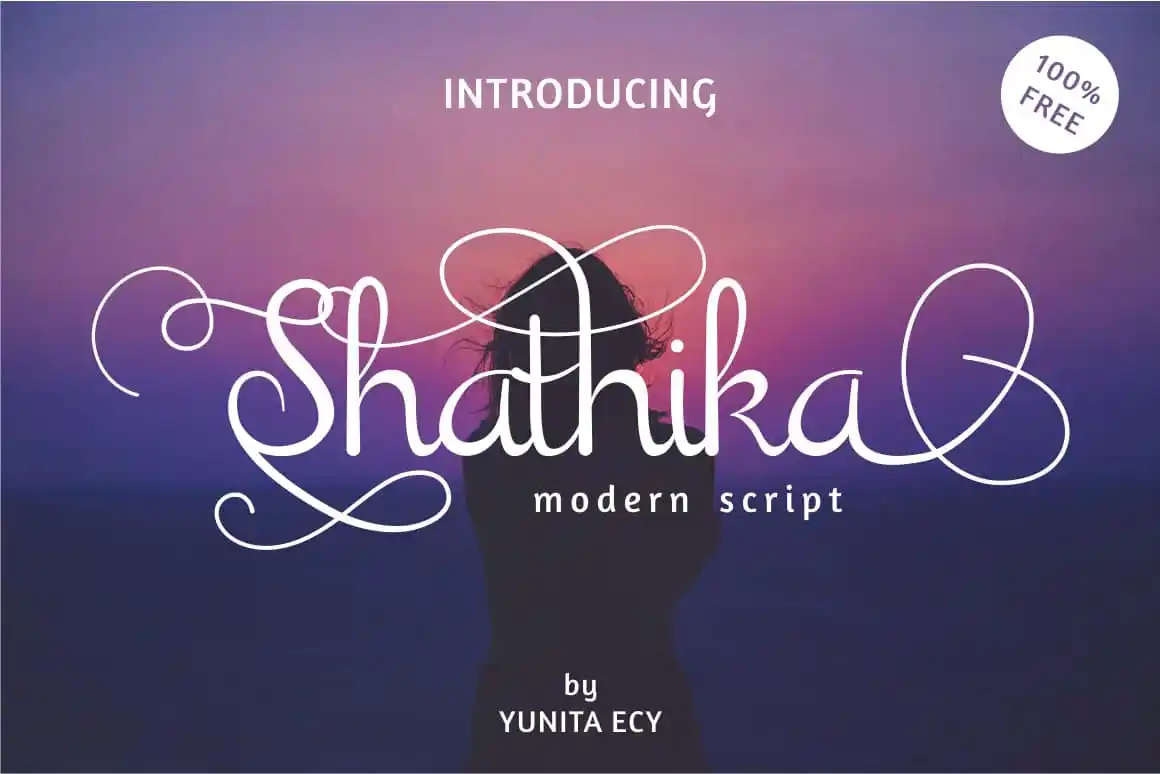
Introduzimos Shathika Script Font, uma nova elegante tipografia moderna de script, perfeitamente projetada para criar letras com estilo e sofisticação. Esta font é a escolha perfeita para aquela necessidade criativa que busca adicionar um toque diferenciado e único a seus materiais gráficos. Shathika foi desenvolvida pelo designer Yunita Ecy, concebida como uma modernização refinada de uma calligrafia artesanal. Seja para cards de aniversário, materiais de marca ou cartões postais, business cards e até mesmo desenhos de logotipo ou blogs, esta font irá complementar suas criações de forma perfeita. Ela oferece um leque amplo de possibilidades, permitindo que você personalize e personalize ainda mais seus trabalhos. Seja para criar o design ideal de seu logo, blog, material de escritório, campanha publicitária ou revista, Shathika Script Font está aqui para ajudar a tornar suas ideias visíveis. Com sua elegância e facilidade de uso, você não precisará se preocupar em ter problemas com layout ou estilo. Você apenas precisa de uma mão habilidosa para criar algo único e poderoso. Não hesite em experimentar Shathika Script Font – é um ótimo investimento para seus materiais gráficos.